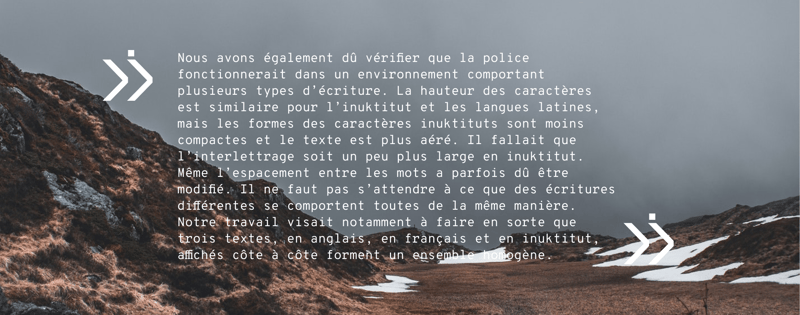
Les nouvelles technologies transforment les modes de communication, mais la généralisation de leur usage risque de donner lieu à une mondialisation néfaste de la culture. Selon certaines estimations, une langue du monde disparaît toutes les deux semaines. Nous devons agir si nous souhaitons que les langues en voie de disparition continuent d’exister. Mais que pouvons-nous faire ?
L’un de nos utilisateurs de Suitcase Fusion a peut-être des pistes intéressantes. Il a travaillé sur un projet de développement de la police Fedra Sans Inuktitut.
L’inuktitut est l’une des langues des Inuits, au Canada. Au 19e siècle, le missionnaire James Evans a créé un syllabaire, ensemble de caractères représentant des syllabes, pour fournir un système d'écriture à certaines langues autochtones d’Amérique, dont le cree, l’ojibwé, puis l’inuktitut.
Au fil des décennies, les locuteurs natifs de l'inuktitut ont adapté ce syllabaire, mais face à l’essor des langues coloniales du Canada (français et anglais), l’usage oral et écrit de l’inuktitut a connu une forte baisse.
L’Institut culturel Avataq a chargé la fonderie Typotheque, spécialisée dans les polices pour des langues diverses, de numériser l’inuktitut écrit et de créer une police qui pourrait être téléchargée et utilisée au quotidien.
J'ai eu la chance de discuter avec Peter Bil’ak de Typotheque au sujet du projet Fedra Sans Inuktitut et de certains des objectifs singuliers de la fonderie.
Avant d'aborder le travail de Typotheque et le projet Inuktitut Fedra Sans, pourriez-vous me dire quelques mots sur ce qui vous a amené à vous intéresser à la typographie.
Peter Bil’ak : Je me suis toujours intéressé à l’étude des textes sous différents angles et à la façon dont la typographie permet l’expression d’une langue. Au-delà de l'écriture des mots, la typographie traduit toutes les nuances d’émotions d'une langue.
À l'oral, nous disposons de nombreuses indications, comme un accent, un bruit de fond ou d'autres éléments que l'on ne retrouve pas sur le papier. Les caractères et les typos peuvent aussi apporter certains compléments d'information. Je m’intéresse à l'aspect personnel et affectif de la typographie.
Je vis dans un petit pays [les Pays-Bas], où nous sommes exposés à plusieurs langues. Je n’ai qu'à faire une heure de route dans une direction ou une autre pour me retrouver dans un environnement linguistique différent. Je suis entouré de langues et de cultures diverses, et je souhaite préserver cette diversité culturelle.
Ces 15 ou 20 dernières années, mes activités professionnelles m'ont apporté une grande ouverture culturelle. J'ai créé une entreprise en Inde dédiée aux langues indiennes. Une autre de nos sociétés se consacre au développement de polices de caractères arabes. Nous avons travaillé sur la plupart des langues vivantes du monde ! C’est toujours passionnant de découvrir comment elles fonctionnent. Il existe déjà des centaines de milliers de polices disponibles pour l'alphabet latin, mais il reste encore beaucoup à faire dans les langues qui n’utilisent pas cet alphabet.
Je veux qu’ils sachent que leurs créations dépendent en partie de leurs outils. Les outils numériques nous offrent des possibilités plus étendues que les méthodes traditionnelles. Toutefois, on se borne parfois trop aux seules fonctionnalités des logiciels que l’on possède, sans réussir à s’en libérer pour innover.
Quand vous prenez conscience de certaines restrictions logicielles et que vous vous retrouvez coincé parce que vous ne pouvez pas concrétiser votre idée géniale dans l’outil que vous avez l’habitude d'utiliser, vous commencez à réfléchir à ce dont vous avez besoin pour réaliser votre projet. C’est ainsi que nous en sommes venus à développer nos propres outils.
Quand nous avons commencé à travailler sur l’arabe, aucune application logicielle toute faite ne permettait de créer des polices arabes sur un Mac. L'arabe ne s’écrit pas de gauche à droite. La ligne de base change souvent et le crénage est impossible parce que tous les principes de crénage reposent sur les mesures typographiques des langues romanes. Cela signifie que les concepteurs dessinaient moins de polices arabes et que nous devions nous servir de nos propres outils pour les créer.
À présent, nous travaillons sur des polices arméniennes, qui sont destinées à un seul pays, à une seule langue et à une seule écriture. Nous en avons créé 20, avons mené des recherches historiques et nous aimerions publier des essais sur nos processus. Nous souhaitons produire quelque chose de vraiment inédit.
Nous avons déjà bien avancé, mais tout n’est pas encore terminé.